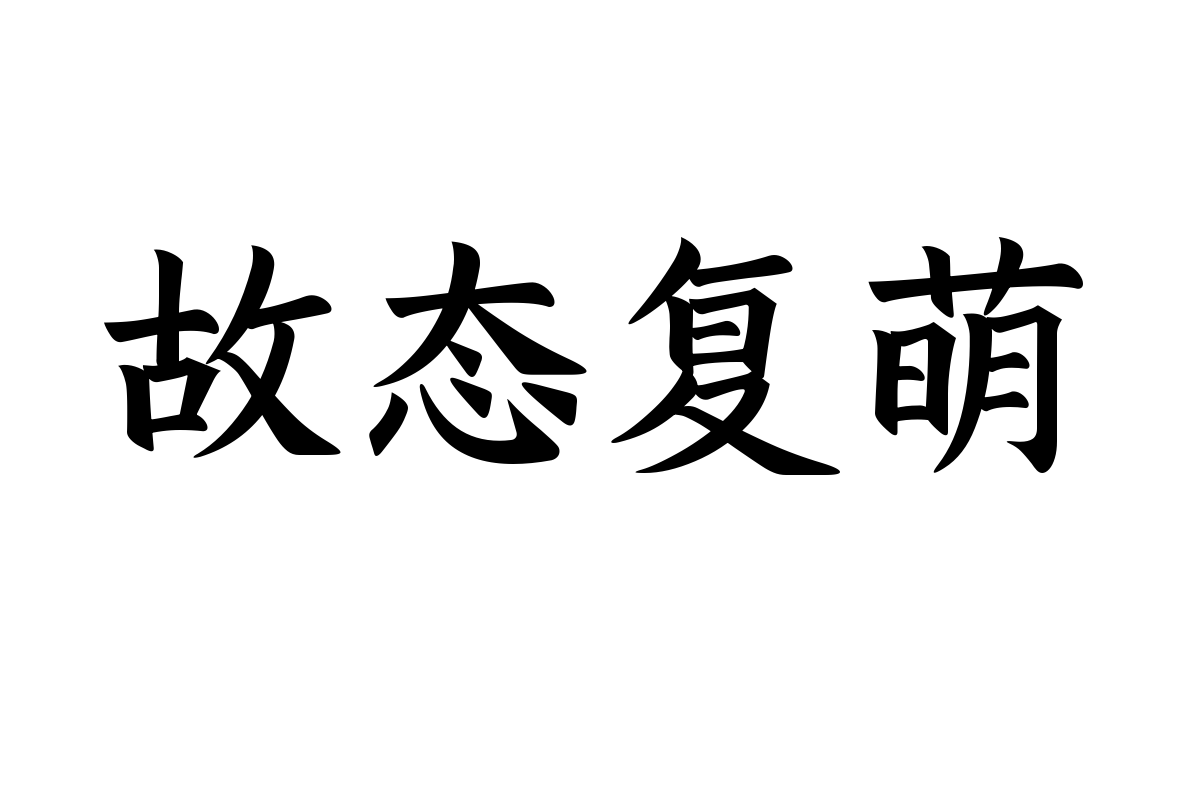
三极古拙楷书简是一种古老的书法字体,源自中国。这种字体的特点是笔画粗犷、厚重,线条流畅自然,具有很高的艺术价值和历史价值。它的字形结构严谨,笔画粗细变化丰富,既有刚劲有力的线条,也有柔和细腻的曲线,给人一种古朴典雅的感觉。
在书写时,三极古拙楷书简需要注意笔画的粗细变化和结构的平衡,以达到字迹清晰、美观的效果。这种字体在古代文学、书法、绘画等领域都有广泛的应用,是研究中国古代文化的重要资料之一。